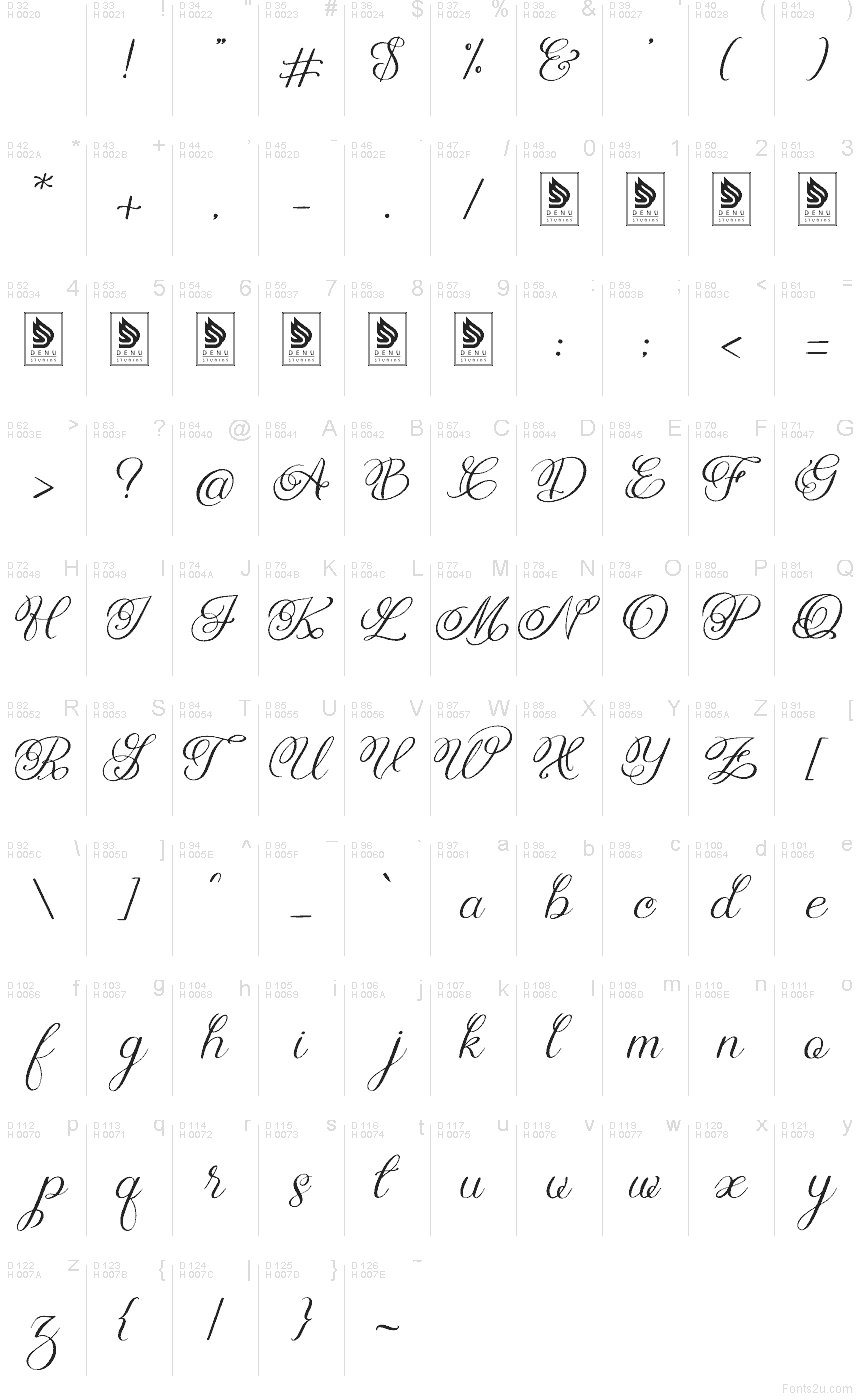
Rellydon 字体
Rellydon
Denustudios
Dede Nugraha
Rellydon 由 Denustudios 设计,是一款免费的书法字体,具有正式邀请函那种轻盈、回环的优雅感。该字体依托于修长、富有弹性的曲线和慷慨的装饰笔触;大写字母奠定了基调,而小写字母则在保持线条流畅的同时带有一丝戏剧感。
它非常适合用于婚礼请柬、美妆品牌、精品包装、杂志标题以及需要体现手绘雅致感的优美语录图形。作为一款免费字体,Rellydon 也非常适合标题、卡片和字母组合设计,其舒展的环形笔画为短名称和标题增添了自然的装饰效果。
Rellydon 由 Denustudios 设计,是一款免费书法字体。